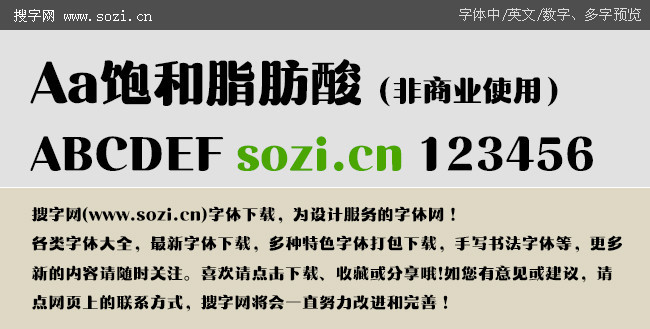
Aa飽和脂肪酸
搜字網(wǎng)給大家提供一款A(yù)a飽和脂肪酸(非商業(yè)使用)中文字體下載,該字體是一款可愛標題藝術(shù)字體,通過對部分筆型的特殊處理,使字面空間分布更加均勻,風格比一般的字體更有特色,連貫字跡顯得干練而不凌亂,清新簡明。適合書裝設(shè)計、包裝設(shè)計、海報設(shè)計等應(yīng)用(此字體為個人非商用版,商用可以聯(lián)系QQ:1006760504)。